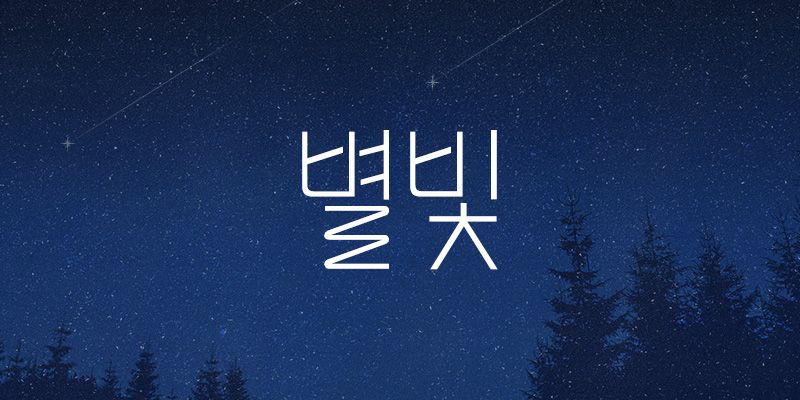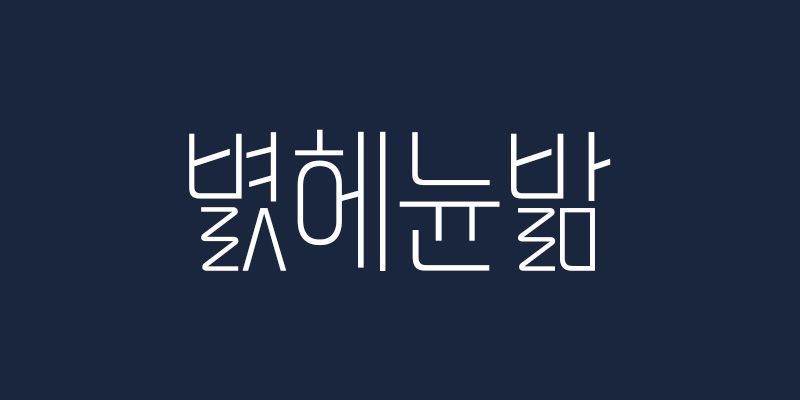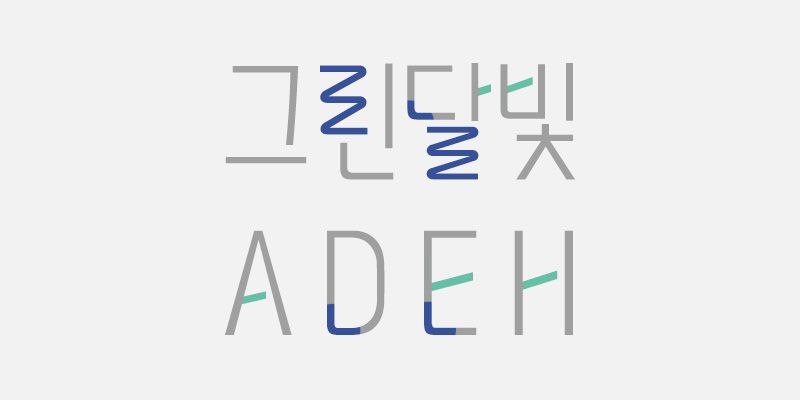
RixStarlight est une police aux formes uniques, en zigzag.
Les caractères ne ressortent pas de manière excessive, afin de maintenir l’équilibre entre l’épaisseur et la modularité. Les grands caractères dégagent une impression de modernité, tandis que les traits obliques confèrent à la police une sensation de vitesse. La police dans son ensemble est exprimée pour s’harmoniser avec diverses courbes.